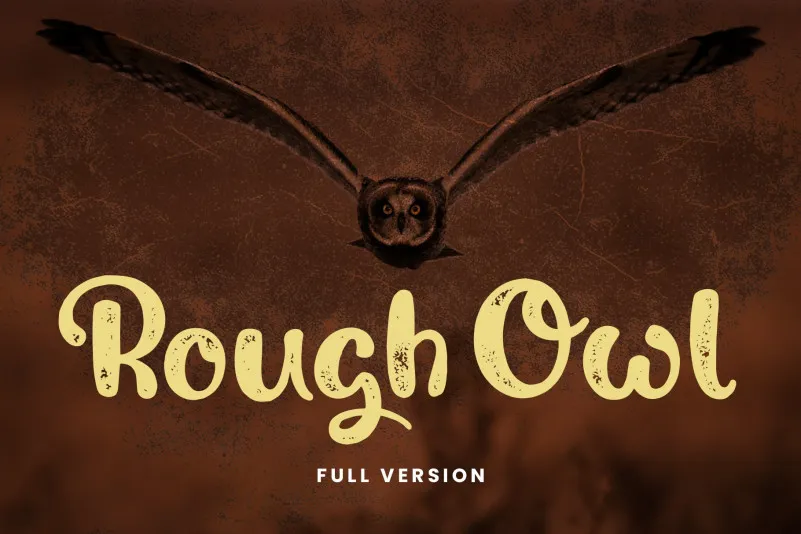
Rough Owl Font – Download Grátis
A fonte Rough Owl é uma escolha perfeita para quem busca um equilíbrio entre modernidade vintage e elegância natural. Esta fonte moderna vintage não apenas oferece linhas robustas, mas também uma aparência elegante e sofisticada que tornam Rusty look estilosamente classe e moderno. Ainda mais interessantes é o fato de que, caso goste desta demonstração, você pode adquirir a versão completa que inclui números, símbolos, caracteres especiais e suporte para várias linguas baseadas no latim. O que torna a Rough Owl ainda mais única são as ligaturas e os gílos alternativos, que aparecem automaticamente enquanto escreve, conferindo um realismo característico da escrita de mão. Em resumo, se você procura uma fonte com estilo vintage moderno, a Rough Owl é definitivamente algo que não pode ser deixado de lado.